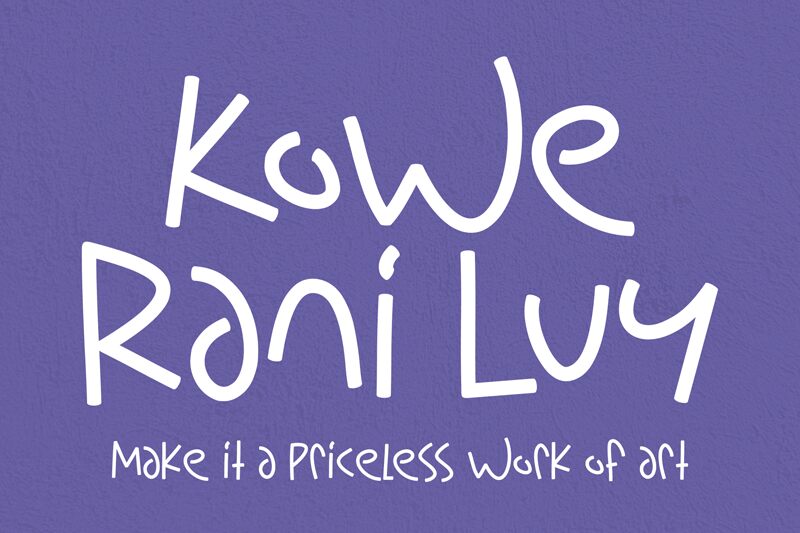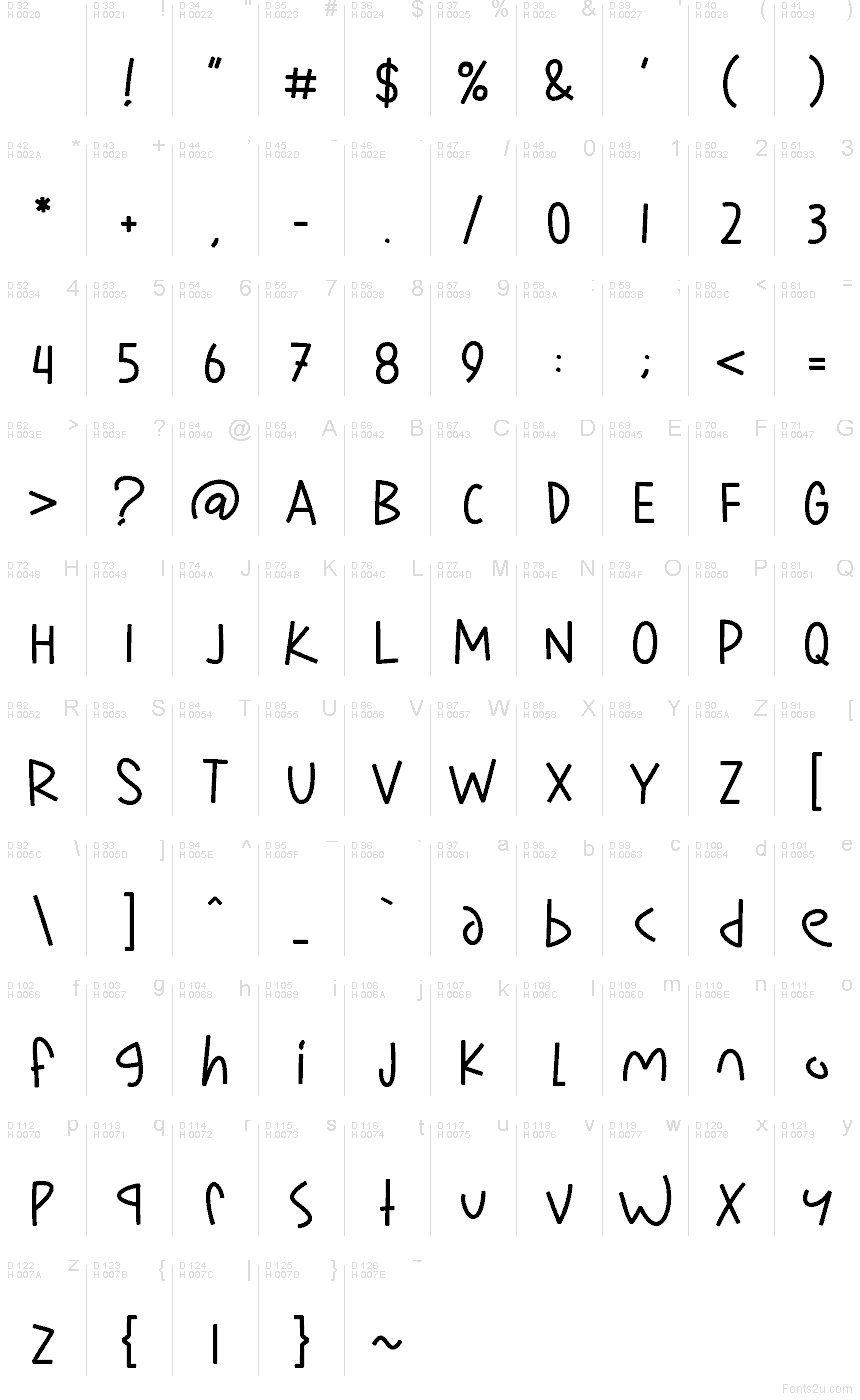
Kowe Rani Luy od Mabhal Studio to darmowy krój pisma w stylu komiksowym o luźnym, ręcznie rysowanym charakterze. Litery opierają się na dużych łukach, przewiewnych odstępach i lekko nieregularnych pociągnięciach, co nadaje im swobodny i nieco psotny klimat – bardziej przypominający szybki napis markerem niż dopracowany tytuł z kreskówki.
Ten swobodny rytm świetnie pasuje do zabawnego brandingu, okładek książek dla dzieci, menu kawiarni, naklejek czy nagłówków w mediach społecznościowych, gdzie ludzki, nieszablonowy akcent liczy się bardziej niż ścisła formalność. Jako darmowy font, sprawdza się szczególnie dobrze w krótkich nagłówkach i szyldach, ponieważ szerokie zawijasy i zaokrąglenia nadają nawet kilku słowom żywy, konwersacyjny kształt.